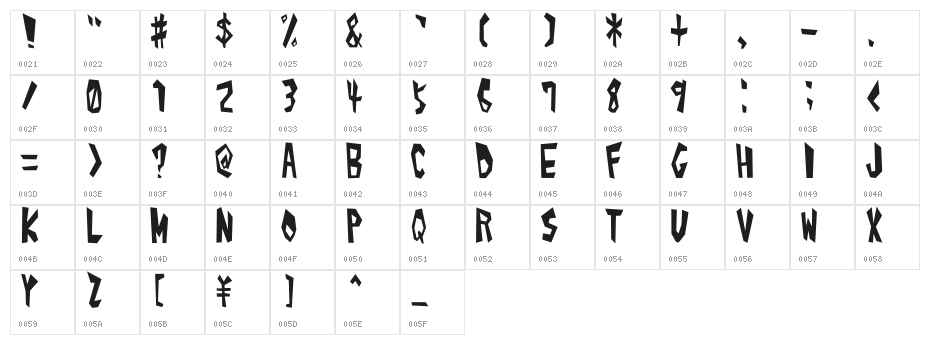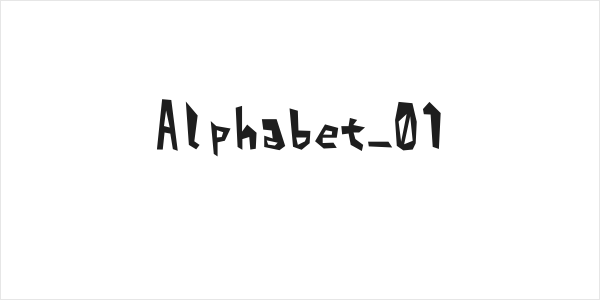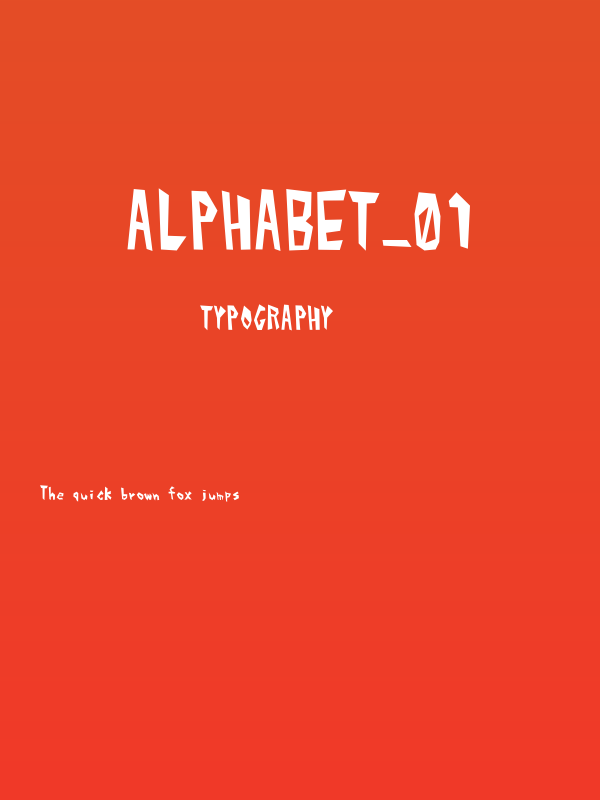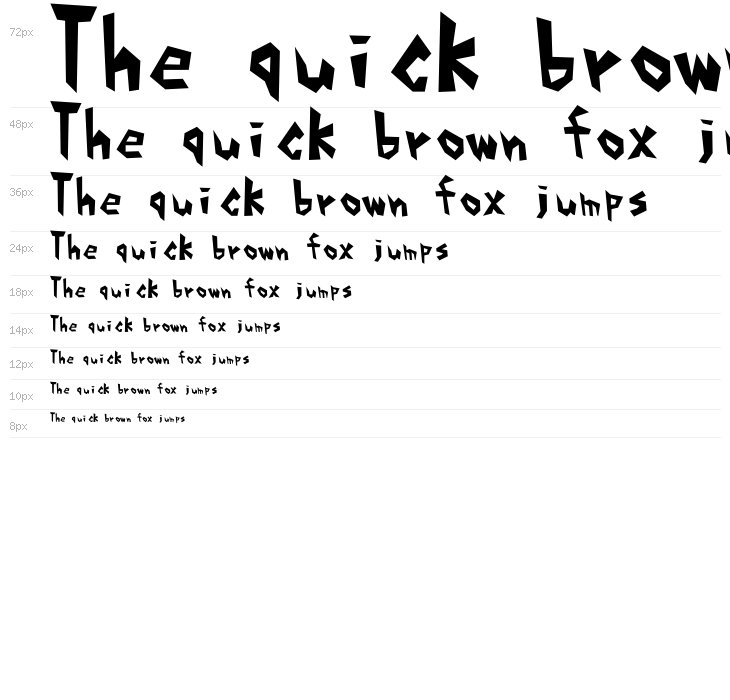
Alphabet_01 Font
✎ Quirky
| 分类 | Quirky |
| 整体风格 | Modern, Artistic |
| 推荐项目 | Ideal for posters, album covers, graffiti art, and any project requiring a bold, artistic statement. |